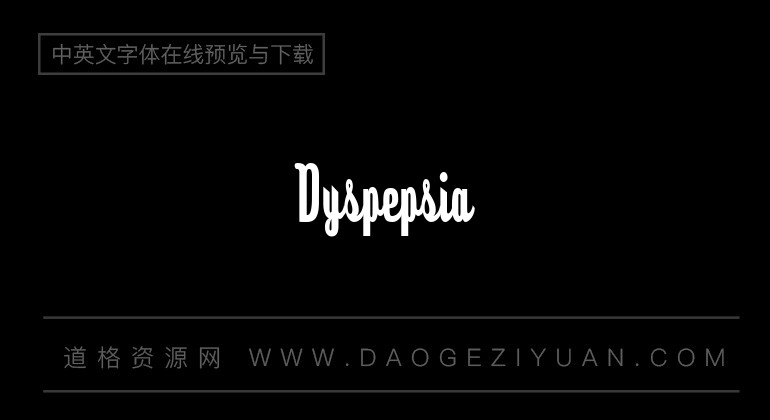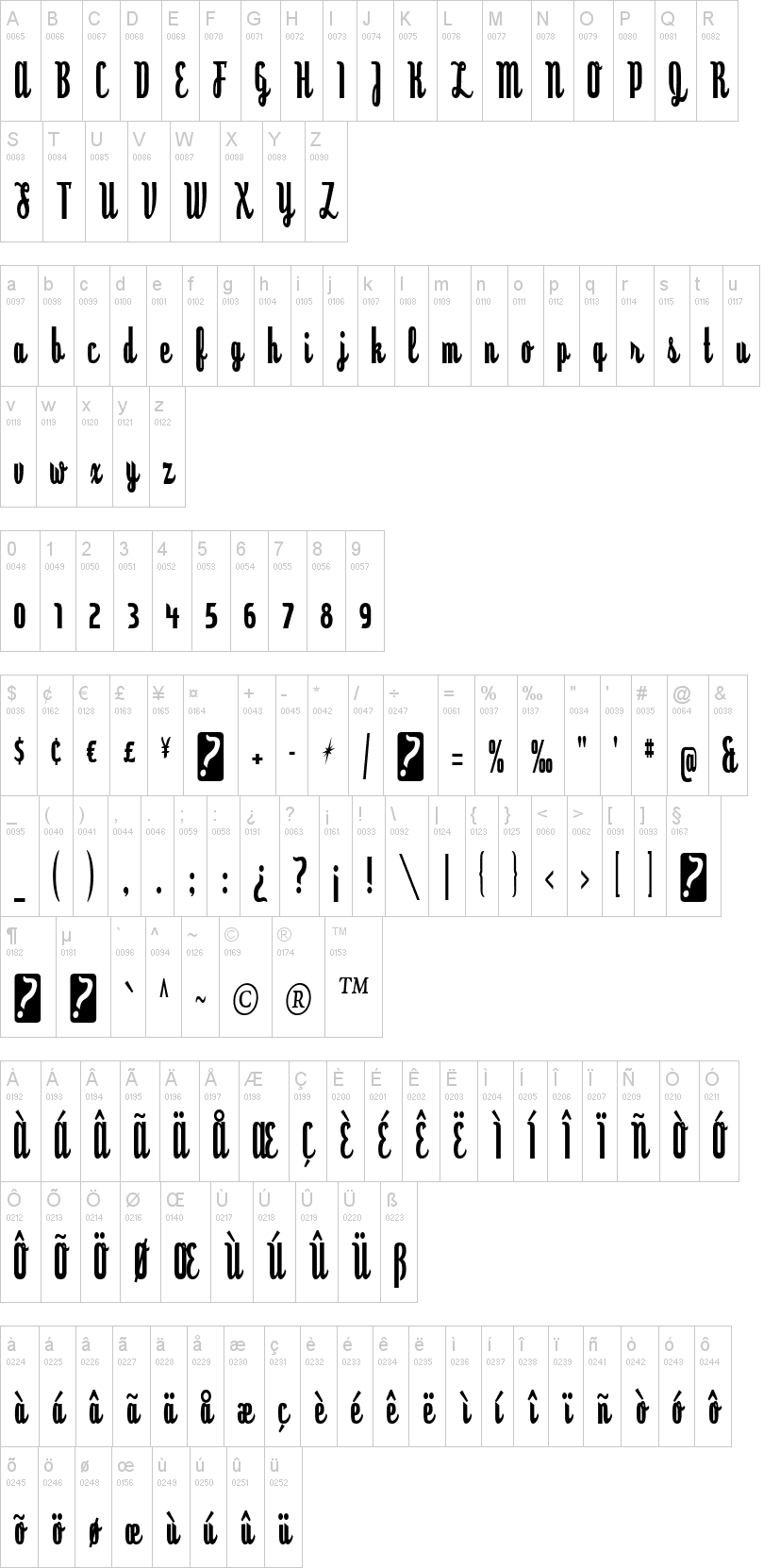
? Dyspepsia是一种极具表现力的英文字体,由英国设计师Dan Rhatigan于2016年设计。它有着粗犷的线条,可以用来创造出鲜明的视觉效果,而且还有丰富的字形变体,可以满足不同的设计需求。Dyspepsia的字形有着极强的表现力,可以用来创造出非常有趣的文字效果,是一款非常适合用于创意文字设计的字体。内容介绍
Dyspepsia是一款非常不错的手写艺术字体,具有很好的视觉感,适合于文化类的宣传设计、商业类品牌的广告和产品包装设计以及个性化文字排版等较多场景。